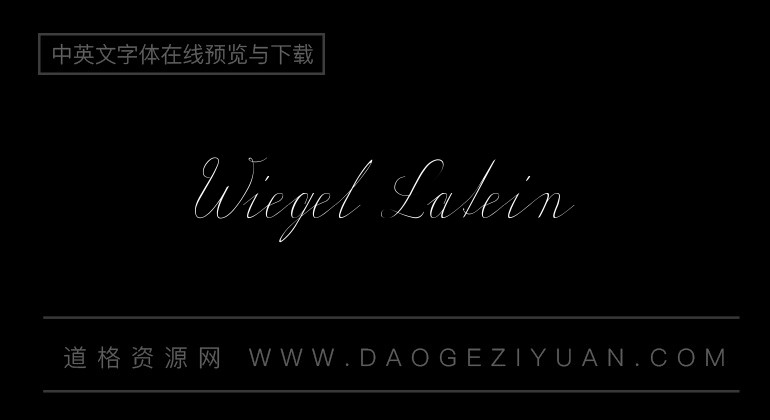
Wiegel Latein 是一款现代拉丁文字体,它的特点是简洁、精致、细腻,字体的设计灵感来自于19世纪的文字,同时也借鉴了古典文字的精髓,使其具有极佳的读写性能。Wiegel Latein 字体具有良好的可读性,它的行距较宽,字体的笔画清晰,可以帮助读者更容易的理解文字的内容。此外,它还具有较强的国际化特性,可以在不同的语言环境中使用,比如德语、英语、法语等。内容介绍
Wiegel Latein是一款非常不错的手写艺术字体,具有很好的视觉感,适合于文化类的宣传设计、商业类品牌的广告和产品包装设计以及个性化文字排版等较多场景。